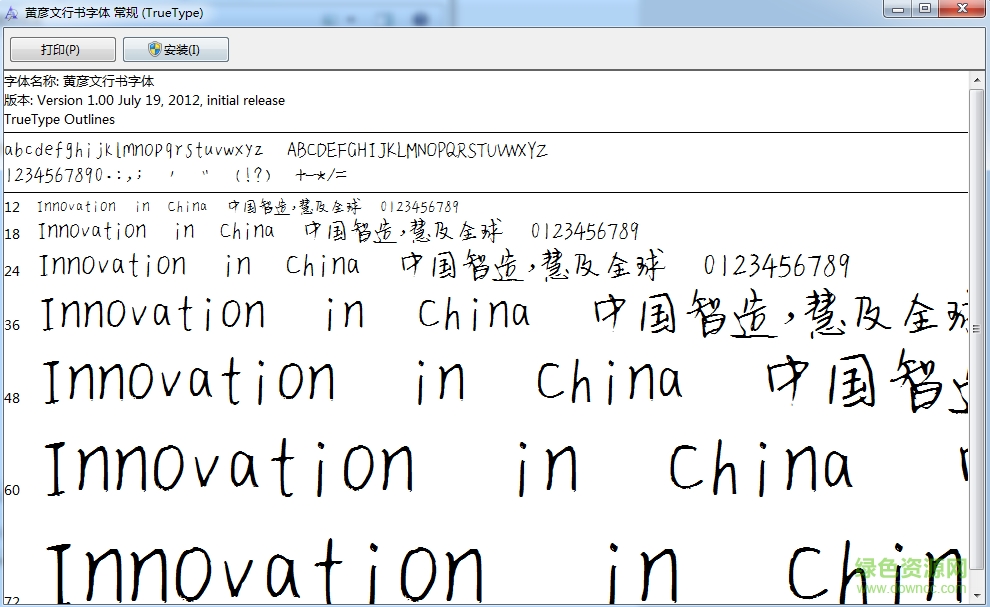
黃彥文行書字體是一款行書書法的手寫體,干凈利落的筆觸讓文字排版更顯飄逸灑脫,很有行書美感,喜歡的朋友快來綠色資源網(wǎng)免費下載吧!
黃彥文行書介于楷書、草書之間的一種字體,是為了彌補楷書的書寫速度太慢和草書的難于辨認而產(chǎn)生的。行書沒有楷書的死板,沒有草書的潦草,更有個性特色。
黃彥文行書字體瀟灑俊逸,該字體適用于文學雜志、宣傳海報、出版印刷等各類美工設(shè)計領(lǐng)域,幫你更好的完成制作設(shè)計工作。